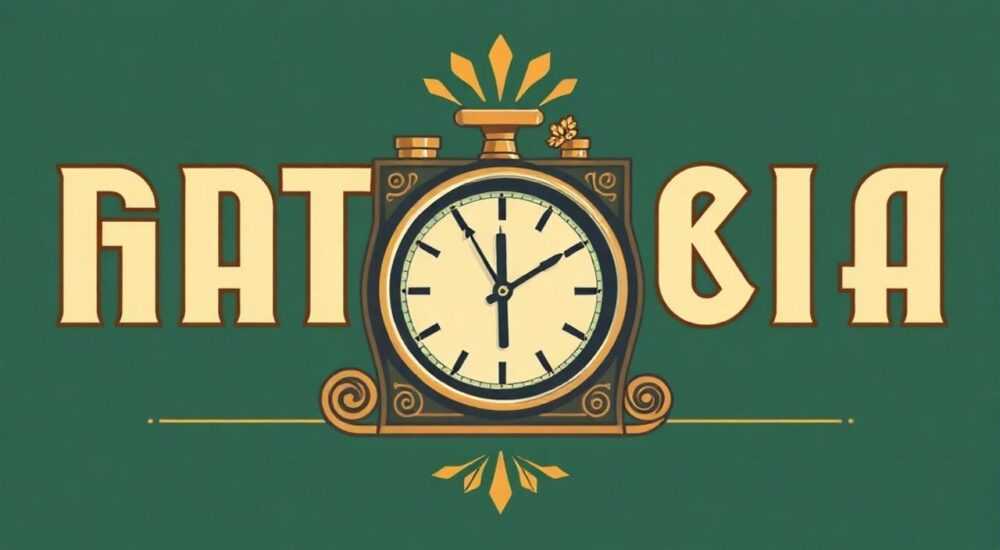
Ар деко шрифт кириллица
Стиль ар-деко, зародившийся в начале XX века, продолжает вдохновлять дизайнеров по всему миру. Его отражение в типографике — особенно при работе с кириллицей — представляет собой сложную задачу, сочетающую историческую точность и современные требования. Ар деко шрифт кириллица — это не просто модный тренд, а полноценный инструмент для создания эффектных брендов, упаковки, интерьеров и цифровых проектов. Главное — понимать его особенности, выбирать или разрабатывать шрифты с учётом контекста и соблюдать баланс между декоративностью и читаемостью.
Ар деко шрифт кириллица сочетает геометрическую строгость, стилизованные элементы и роскошь 1920–30-х годов. Для успешного применения выбирайте качественные шрифты с хорошей проработкой начертаний или закажите кастомную разработку под проект.
Что такое ар-деко шрифт: основные черты стиля
Ар-деко (от французского «Art Décoratif») — это стиль, достигший пика популярности в 1920–1930-х годах. Он символизировал прогресс, роскошь и оптимизм новой эпохи. В типографике это нашло отражение в строгих, но выразительных формах букв. Шрифты ар-деко отличаются геометричностью, симметрией, использованием углов, линий и абстрактных элементов. Часто они напоминают небоскрёбы, орнаменты или механизмы.
Типичные характеристики включают высокие x-высоты, узкие пропорции, вертикальную ориентацию и минимальное количество засечек. Многие шрифты имеют ступенчатые окончания штрихов, радиальные формы, асимметричные детали и декоративные завитки. Цветовая палитра часто ограничивается контрастными сочетаниями: чёрный на белом, золото на тёмном фоне, серебро и бронза.
В западной типографике ар-деко хорошо представлен такими шрифтами, как Bifur, Broadway, Art Deco New, DecoType. Однако применительно к кириллице ситуация сложнее. Русский алфавит имеет больше символов, некоторые из которых (например, «ж», «щ», «э») трудно адаптировать к жёсткой геометрии ар-деко без потери узнаваемости.
Полезно знать: Ар-деко шрифты часто используются в сочетании с другими элементами стиля — геометрическими узорами, линиями, солнечными лучами, хромированными текстурами.
Ключевые визуальные признаки
• Высокая вертикальная ориентация букв, имитирующая небоскрёбы.
• Ступенчатые или скошенные окончания штрихов, напоминающие архитектурные элементы.
• Геометрические формы: круги, треугольники, ромбы — в составе букв или как часть орнамента.
• Минимализм в деталях, но с акцентом на роскошь через материалы (в полиграфии — фольгирование, тиснение).
• Использование капительных (прописных) букв, особенно в заголовках.
Особенности кириллицы в стиле ар-деко
Работа с кириллицей в стиле ар-деко требует особого подхода. Русский алфавит содержит 70 символов (включая строчные, прописные, знаки препинания), многие из которых не имеют аналогов в латинице. Это усложняет процесс адаптации стиля, поскольку необходимо сохранить как эстетику, так и функциональность.
Одна из главных проблем — асимметрия некоторых букв. Например, буква «щ» имеет сложную структуру с двумя хвостами, что затрудняет её встраивание в строгую геометрию ар-деко. Аналогично — «ж», «э», «ы». Дизайнеры решают это либо упрощением форм, либо добавлением декоративных элементов, компенсирующих дисбаланс.
Ещё одна сложность — отсутствие исторических прототипов. В СССР 1920–30-х годов господствовал конструктивизм, который, хотя и близок к ар-деко, был более утилитарным. Поэтому современные ар-деко шрифты для кириллицы — это, как правило, ретро-интерпретации, вдохновлённые европейскими и американскими образцами.
«При проектировании ар-деко шрифта для кириллицы важно не переусердствовать с декором. Один избыточный завиток может испортить всю композицию. Лучше сделать акцент на форме, чем на украшении.» — Алексей К., типографический дизайнер
Проблемы и решения
1. Несоответствие пропорций. Некоторые буквы слишком широкие («ш», «щ»), другие — узкие («и», «л»). Решение — унификация ширины в моноширинном варианте или создание гармоничной системы интервалов.
2. Читаемость в мелком размере. Декоративные элементы теряются. Рекомендуется использовать такие шрифты только для заголовков и логотипов.
3. Отсутствие курсива и дополнительных начертаний. Большинство ар-деко шрифтов для кириллицы существуют только в одном весе. Выход — заказ кастомной разработки.
Буква
Проблема
Решение
Ж
Сложная форма с тремя вертикалями
Упрощение до двух колонн с горизонтальной перекладиной
Щ
Двойной хвост нарушает симметрию
Один хвост оформлен как ступенька, второй — укорочен
Э
Закруглённая форма противоречит геометричности
Замена на многоугольник с фасками
Ы
Нижний хвост создаёт дисбаланс
Обрезка хвоста или его интеграция в общий орнамент
Популярные шрифты для русского текста в духе ар-деко
На рынке существует ограниченное, но растущее число шрифтов, поддерживающих кириллицу и выполненных в духе ар-деко. Ниже — проверенные варианты, подходящие для профессионального использования.
• DecoType Cyrillic — адаптация классического DecoType, с проработанными формами для всех кириллических символов. Отличается высокой x-высотой и ступенчатыми окончаниями.
• Neon Lights — вдохновлён неоновыми вывесками 1930-х. Поддерживает кириллицу, но рекомендуется только для заголовков.
• Art Deco Pro — коммерческий шрифт с полной поддержкой русского языка. Имеет несколько начертаний, включая светлое и жирное.
• Soviet Deco — гибрид советского конструктивизма и ар-деко. Уникален тем, что использует элементы пропагандистской графики.
• Luxor — бесплатный шрифт с египетскими мотивами (часто встречающимися в ар-деко). Подходит для логотипов и оформления мероприятий.
Где скачивать и покупать
• MyFonts — крупнейшая платформа для лицензионных шрифтов. Поиск по ключевым словам: «art deco + cyrillic».
• FontShop — предлагает профессиональные наборы с гарантией качества.
• Adobe Fonts — встроен в Creative Cloud, позволяет тестировать шрифты перед покупкой.
• Lost Type Co-op — нишевый ресурс с авторскими работами, включая редкие ар-деко шрифты.
• Google Fonts — бесплатные шрифты, но выбор для ар-деко с кириллицей крайне ограничен.
Полезно знать: Перед использованием шрифта проверьте лицензию. Некоторые бесплатные шрифты запрещают коммерческое использование или требуют указания авторства.
Где и как использовать ар-деко шрифт кириллица
Ар-деко шрифт — не универсальное решение. Его стоит применять там, где нужно подчеркнуть статус, роскошь, историческую глубину или театральность. Ниже — ключевые сферы использования.
• Брендинг и логотипы. Особенно эффективен для отелей, ресторанов, ювелирных брендов, барбершопов, винных марок. Пример: логотип бара в стиле «Гэтсби» с золотым тиснением и вертикальной компоновкой букв.
• Упаковка. Парфюмерия, шоколад, коньяк — продукты, где важна эстетика. Шрифт создаёт ощущение наследия и эксклюзивности.
• Интерьеры. На стенах, вывесках, меню. Хорошо смотрится на матовых поверхностях с подсветкой.
• Полиграфия. Приглашения на свадьбы, вечеринки в стиле ретро, афиши. Используйте тиснение фольгой для максимального эффекта.
• Цифровые проекты. Сайты, презентации, баннеры. Ограничьте использование — только заголовки, не более 5–7 слов.
Правила компоновки
1. Не комбинируйте два декоративных шрифта. Ар-деко должен быть единственным акцентом.
2. Используйте простые, нейтральные шрифты для основного текста (например, Helvetica, PT Sans).
3. Оставляйте много свободного пространства вокруг надписи — это усиливает эффект роскоши.
4. Применяйте контрастные цвета: белый на чёрном, золото на тёмно-синем, серебро на бордовом.
5. Добавьте текстуры: мрамор, хром, дерево — для усиления атмосферы.
«Лучше один раз увидеть, чем сто раз прочитать. Создайте мудборд с примерами настоящих ар-деко объектов — от вывесок Нью-Йорка до интерьеров пароходов. Это поможет точно передать стиль.» — Марина Т., арт-директор
Ошибки при использовании и как их избежать
Даже опытные дизайнеры допускают просчёты при работе с ар-деко шрифтами. Вот самые распространённые ошибки и пути их устранения.
1. Переоценка читаемости
Многие ар-деко шрифты плохо читаются в мелком размере. Использование их для длинных текстов приводит к снижению восприятия.
Решение: применяйте только для заголовков, логотипов, коротких слоганов.
2. Несоответствие контексту
Шрифт ар-деко будет выглядеть странно на сайте детского сада или мобильном приложении для фитнеса.
Решение: анализируйте целевую аудиторию и сообщение бренда. Стиль должен поддерживать, а не противоречить ему.
3. Отсутствие технической подготовки
Некоторые шрифты скачиваются без кириллических символов или с битыми глифами.
Решение: всегда проверяйте шрифт в программе (Illustrator, Photoshop), открывая все символы.
4. Игнорирование лицензии
Использование коммерческого шрифта без лицензии грозит штрафами.
Решение: покупайте шрифты на официальных площадках или используйте бесплатные с разрешением на коммерцию.
5. Избыточное украшение
Добавление теней, градиентов, обводок «для красоты» может перегрузить композицию.
Решение: доверьтесь самому шрифту. Если он хорошо спроектирован — ему не нужны дополнительные эффекты.
Полезно знать: Проверяйте, как шрифт выглядит в чёрно-белом варианте. Если он теряет выразительность — возможно, он слишком зависит от цвета.
Как создать собственный ар-деко шрифт для кириллицы
Если готовые решения не подходят, остаётся вариант разработки кастомного шрифта. Это дорого, но оправдано для брендов, стремящихся к уникальности.
Процесс включает несколько этапов:
1. Исследование и референсы
Соберите вдохновляющие примеры: старые вывески, плакаты, архитектура, интерьеры. Обратите внимание на линии, углы, пропорции. Создайте доску в Pinterest или Notion.
2. Эскизирование
Начните с карандаша на бумаге. Проработайте ключевые буквы: А, Д, М, Р, Ш, Щ. Затем переходите к сложным: Ж, Э, Ы. Убедитесь, что все формы согласованы.
3. Векторизация
Перенесите эскизы в Illustrator или Glyphs. Используйте сетку 8×8 или 10×10 для контроля пропорций. Уделите внимание межбуквенным интервалам (кернингу).
4. Тестирование
Создайте пробные надписи: «Москва», «Роскошь», «Gatsby». Проверьте читаемость на разных фонах и размерах.
5. Финализация и экспорт
Добавьте недостающие символы (знаки препинания, цифры), настройте метрики, экспортируйте в форматах OTF, WOFF (для веба).
«Начните с 20 самых употребляемых букв. Остальные можно сделать по аналогии. Не пытайтесь сразу нарисовать весь алфавит — это демотивирует.» — Дмитрий Л., типограф
Успешное применение ар-деко шрифта требует не только вкуса, но и системного подхода. Стиль не должен быть самоцелью — он должен служить бренду. Лучшие примеры — когда шрифт становится частью визуального нарратива, рассказывая историю роскоши, стабильности, элегантности.
При выборе шрифта ориентируйтесь не на внешнюю красоту, а на соответствие трём критериям: читаемость, масштабируемость, уникальность. Даже самый красивый шрифт провалится, если буквы сливаются при уменьшении или не подходят по тональности.
Технологии упрощают доступ к качественным шрифтам, но не заменяют дизайн-мышление. Автоматическая генерация шрифтов (AI) пока не способна передать тонкости ар-деко — особенно в кириллице. Здесь важен человеческий контроль, внимание к деталям, понимание культурного контекста.
Развитие 3D-типографики и анимации открывает новые возможности. Представьте логотип, где буквы «вырастают» как небоскрёбы, или анимированное меню с мерцающими неоновыми буквами. Будущее — за интерактивными, адаптивными шрифтами, которые сохраняют дух ар-деко, но работают в цифровой среде.
Можно ли использовать ар-деко шрифт для сайта?
Да, но ограниченно. Только для заголовков, H1, названий разделов. Основной текст должен быть на нейтральном шрифте. Также учитывайте скорость загрузки — тяжёлые шрифты могут замедлить сайт.
Какой шрифт лучше: платный или бесплатный?
Платные шрифты обычно качественнее: лучше проработаны глифы, есть поддержка кириллицы, несколько начертаний, корректная лицензия. Бесплатные — хороши для тестов, но не для коммерческих проектов.
Подходит ли ар-деко для молодёжного бренда?
Да, если бренд играет на контрастах. Например, streetwear с элементами ретро-роскоши. Главное — сохранить актуальность через композицию, цвет, подачу.
Нужно ли точно следовать историческим канонам?
Не обязательно. Современный ар-деко — это интерпретация. Можно смешивать с минимализмом, хай-теком, даже гранжем. Главное — чтобы стиль был осознанным.
Как проверить, поддерживает ли шрифт кириллицу?
Откройте шрифт в программе (например, Font Book на Mac), найдите раздел «Глифы» и проверьте наличие букв «А», «Я», «ж», «э». Также поищите в описании «Cyrillic support».
Ар деко шрифт кириллица — это мощный инструмент визуальной коммуникации. Он соединяет историческую глубину с современной эстетикой, позволяя создавать запоминающиеся бренды и проекты. Однако его применение требует вдумчивости, знания типографики и чувства меры.
Главное — помнить, что шрифт не должен доминировать. Он должен поддерживать идею, усиливать сообщение, а не затмевать его. Успешный дизайн — это баланс между красотой и функциональностью, между декорацией и смыслом.
Выбирая ар-деко шрифт, обращайте внимание на качество начертаний, лицензию, контекст использования. Не бойтесь экспериментировать, но всегда тестируйте результат на реальной аудитории.
• Ар-деко шрифт — это геометрия, симметрия и роскошь, воплощённые в типографике.
• Кириллица требует особого подхода из-за сложности некоторых букв.
• Используйте шрифт только для заголовков и логотипов, избегая длинных текстов.
• Предпочтение отдавайте лицензионным шрифтам с поддержкой кириллицы.
• Для уникальных проектов рассмотрите разработку кастомного шрифта.
Правовая ответственность: решения, принятые на основе опубликованной информации, пользователь принимает самостоятельно и на свой риск; редакция и авторы несут ответственность в пределах, установленных законодательством Российской Федерации.